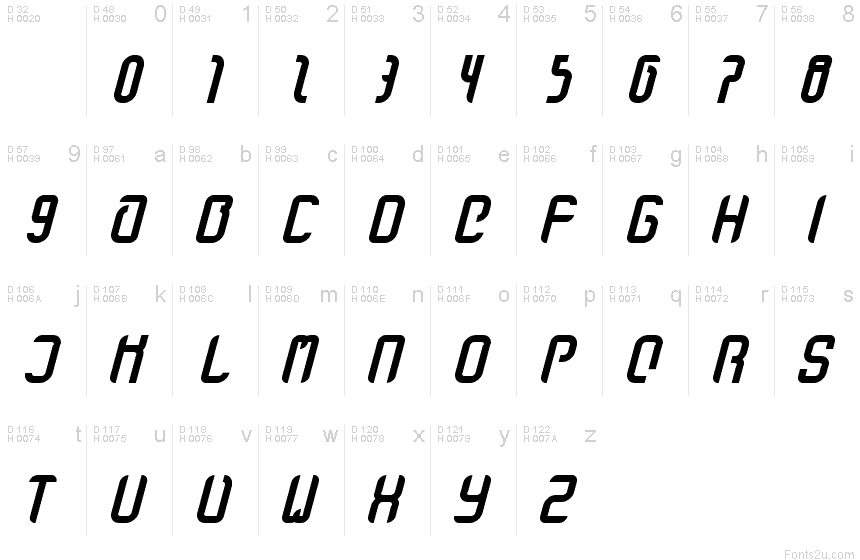
Stanze Fett, autorstwa Helge Barskego, to darmowy, nowoczesny krój displayowy z nutą techno-italiki rodem z końca XX wieku. Litery pochylają się do przodu, wyróżniając się zaokrąglonymi rogami, wyciętymi łączeniami i szerokimi, miękkimi pociągnięciami, dzięki czemu cały krój sprawia wrażenie szybkiego, kompaktowego i lekko mechanicznego, ale nie chłodnego.
Doskonale sprawdza się w nagłówkach plakatów, ulotkach klubowych, okładkach albumów, planszach tytułowych czy brandingu sportowym, wszędzie tam, gdzie w krótkim haśle liczy się dynamika, a nie formalność. Jako darmowy font świetnie nadaje się też do tworzenia logotypów i monogramów – powtarzalny diagonalny rytm i gładkie krawędzie sprawiają, że nawet kilka liter wygląda jak zaprojektowany znak graficzny.